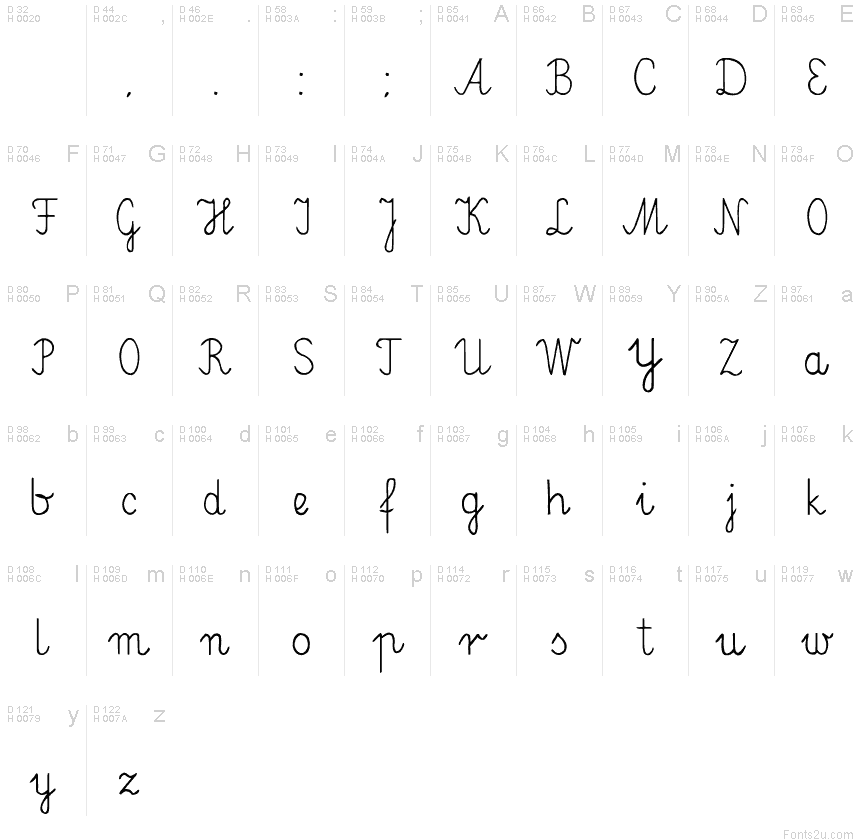
Písmo Elementarz od Bartka Nowaka z czcionki.com je bezplatný font ve školním stylu s hladkou, lehce kreslenou linkou a přirozeným rytmem spojů. Písmena působí jako poctivě napsaný rukopis, nikoliv jako zdobný prvek, díky čemuž dodají nadpisům, pracovním listům, výukovým materiálům, dětským knihám, kartičkám i školnímu brandingu vřelý, ručně psaný nádech.
Elementarz nejlépe vynikne tam, kde hledáte přátelskou dynamiku, která ale není chaotická ani přehnaně roztomilá. Tento bezplatný font se skvěle hodí na plakáty, pozvánky, obaly, grafiku pro sociální sítě nebo výukové aplikace. Nejlépe funguje ve středních až velkých velikostech, ideálně v kombinaci s prostým bezpatkovým písmem pro doplňkový text.